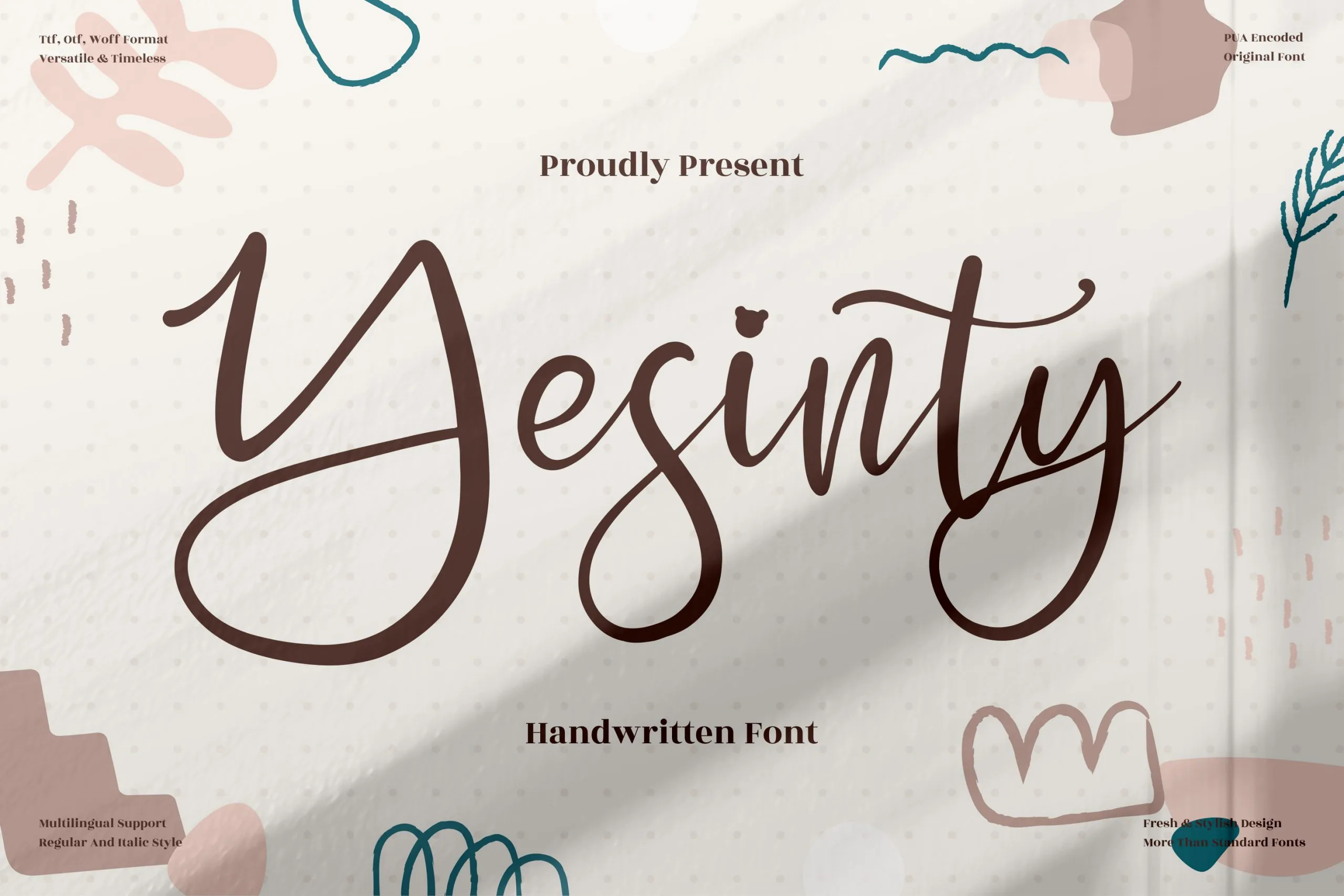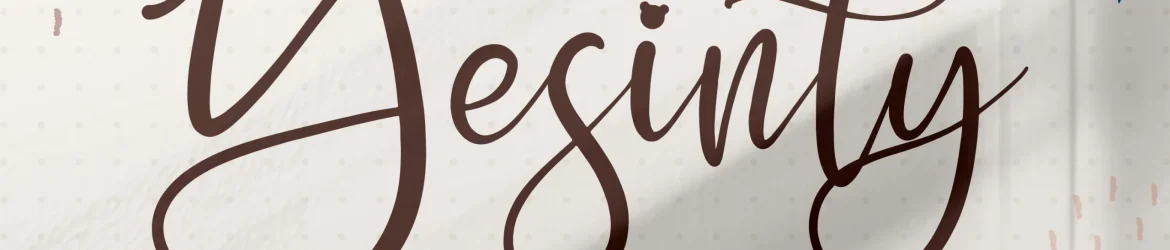
A fonte ‘Yesinty Font’ é uma excelente escolha para projetos que precisam de um toque delicado e pessoal, tanto em pequenos detalhes quanto em elementos visuais mais impactantes. Seja para criar logos ou design de embalagens únicos, seja para trabalhos de arte digital ou editoriais impressos, a Yesinty atinge exatamente o ponto certo de personalidade e elegância que cada projeto pode precisar. Suavemente escrita a mão, esta fonte permite que você incorpore um toque autêntico em uma variedade de aplicativos, desde logomarcas e embalagens até etiquetas e capas de livros. Seja para aqueles projetos onde você precisa algo mais do que apenas letras, mas também de um ar delicado, a Yesinty font é uma fonte perfeita para qualquer tipo de trabalho em gráficos.